Nhiều designer khi tìm kiếm font chữ bay bổng thường gặp tình trạng tải về bản không hỗ trợ tiếng Việt hoàn chỉnh, dẫn đến dấu bị lệch hoặc nét chữ quá mảnh khiến việc in UV hay khắc laser bị đứt nét, nhòe chữ. Chỉ cần sai sót nhỏ trong việc chọn font hoặc xử lý file, sản phẩm quà tặng cao cấp sẽ mất đi sự tinh tế và sang trọng vốn có.
Ở bài viết này, In Viva cung cấp trọn bộ phông chữ bay bổng Việt hóa chuẩn thiết kế, đảm bảo độ hiển thị sắc nét, phục vụ tối ưu cho mọi nhu cầu in ấn và truyền thông thương hiệu.
Để hỗ trợ cộng đồng designer và các doanh nghiệp đang tìm kiếm giải pháp thẩm mỹ cho bao bì, Xưởng In Viva đã tổng hợp những bộ font script, calligraphy xuất sắc nhất. Đây là những phông chữ đã được kiểm tra kỹ về bảng mã Unicode, đảm bảo gõ tiếng Việt không lỗi dấu và hiển thị mượt mà trên các phần mềm.
Danh sách các nhóm font nổi bật trong bộ tải về:
- Nhóm Calligraphy: Các nét thanh nét đậm rõ ràng, tạo cảm giác như viết bằng bút lông, phù hợp cho thiệp mời và hộp quà cao cấp.
- Nhóm Handwriting: Mang phong cách chữ viết tay tự nhiên, gần gũi nhưng vẫn rất nghệ thuật.
- Nhóm Modern Script: Đường nét tối giản hơn, dễ đọc nhưng vẫn giữ được độ “bay” cần thiết cho các thiết kế hiện đại.
Đặc điểm của các phông chữ bay bổng trong thiết kế quà tặng
Việc sử dụng phông chữ bay bổng đòi hỏi sự am hiểu về cấu trúc ký tự để tránh gây rối mắt. Khác với các font không chân cứng nhắc, dòng chữ nghệ thuật thường có các đường nối (ligatures) giữa các chữ cái, tạo nên một dòng chảy thị giác liên tục.
Tại In Viva, khi thiết kế cho khách hàng, chúng tôi nhận thấy các font này đặc biệt hiệu quả khi in ấn trên các sản phẩm dành cho phái đẹp hoặc ngành hàng cao cấp như yến sào, đông trùng hạ thảo, mỹ phẩm. Độ uốn lượn của chữ tạo nên cảm giác thủ công, tinh xảo, giúp nâng tầm giá trị món quà trong mắt người nhận.
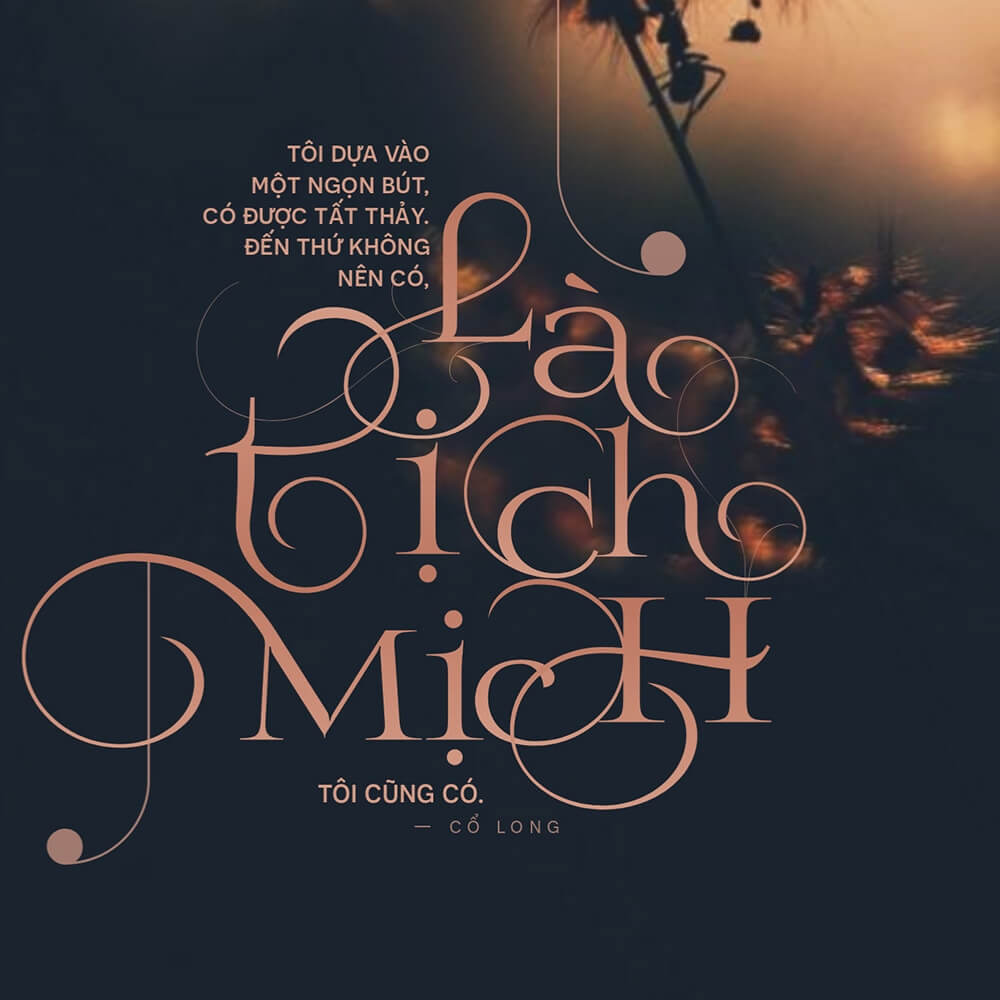
03 lưu ý khi dùng font chữ bay bổng để in ấn
Nếu bạn chỉ thiết kế để đăng mạng xã hội, mọi thứ rất đơn giản. Nhưng khi chuyển sang giai đoạn sản xuất, font bay bổng tiềm ẩn nhiều rủi ro kỹ thuật mà nếu không xử lý khéo sẽ làm hỏng toàn bộ đơn hàng.
Tránh nét quá mảnh khi khắc laser
Khi dùng máy laser để khắc tên lên bình giữ nhiệt kim loại hoặc bút ký, các phông chữ có nét thanh quá mỏng (hairline) thường không hiển thị rõ hoặc dễ bị cháy xém. Lời khuyên của In Viva là bạn nên chọn các biến thể có độ dày vừa phải hoặc thêm một chút “stroke” nhẹ để máy laser có thể đi nét ổn định.
Kiểm tra lỗi chồng nét
Đặc thù của các dòng chữ nghệ thuật là các ký tự thường đè lên nhau. Trong in ấn, nếu bạn không “Weld” hoặc “Unite” các chữ cái lại thành một khối vector duy nhất, tại các điểm giao nhau sẽ xuất hiện các vết cắt hoặc chồng mực không đều, đặc biệt nguy hiểm khi làm khuôn ép kim (hot stamping) trên hộp cứng.
Đảm bảo tính dễ đọc
Đừng quá sa đà vào việc chọn font chữ bay bổng quá rắc rối. Một lỗi phổ biến là designer chọn font có quá nhiều chi tiết uốn lượn cho các thông tin quan trọng như số điện thoại hay địa chỉ trên túi giấy. Điều này gây khó khăn cho khách hàng trong việc tiếp nhận thông tin.
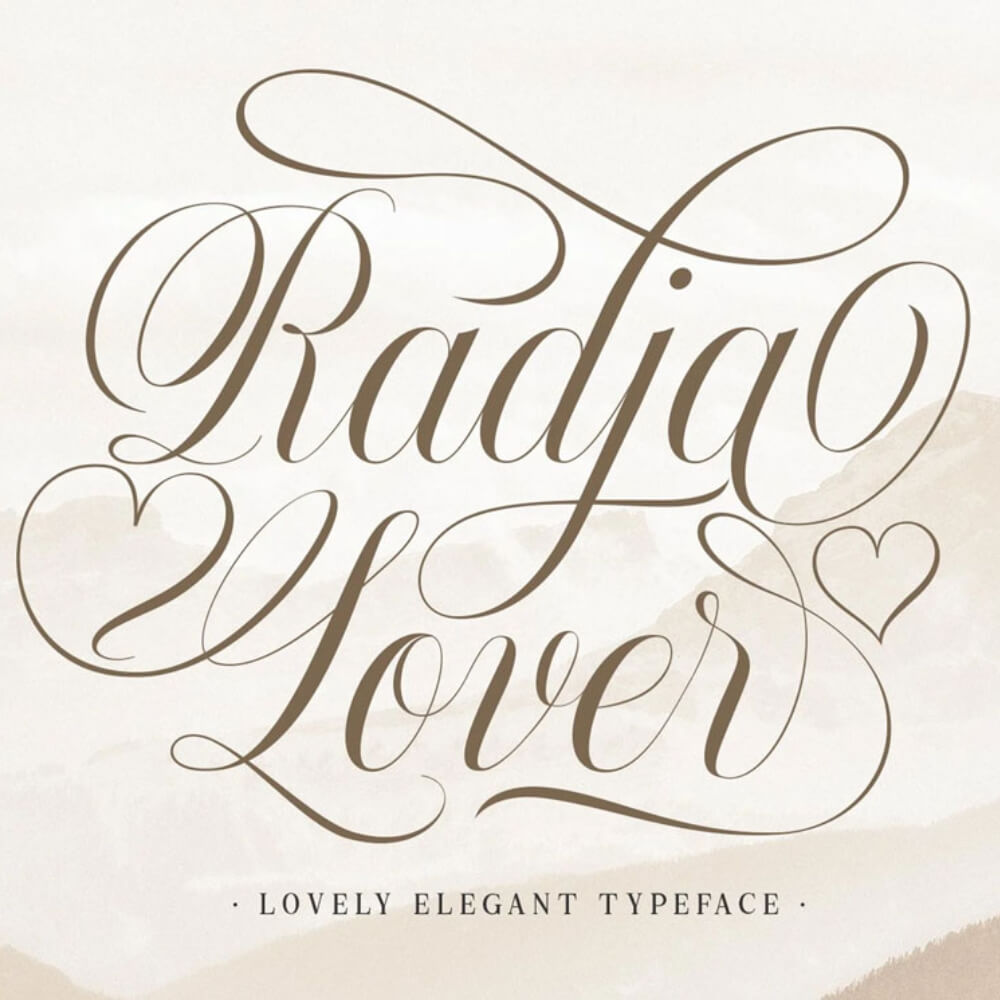
1. Tại sao tôi gõ tiếng Việt bằng font chữ bay bổng lại bị lỗi ô vuông?
2. Có nên dùng phông chữ bay bổng để in địa chỉ trên bao bì không?
Không nên. Các thông tin mang tính chỉ dẫn như địa chỉ, mã số thuế nên dùng font không chân (Sans-serif) để đảm bảo độ rõ ràng. Font nghệ thuật chỉ nên dùng cho tên thương hiệu hoặc slogan ngắn.